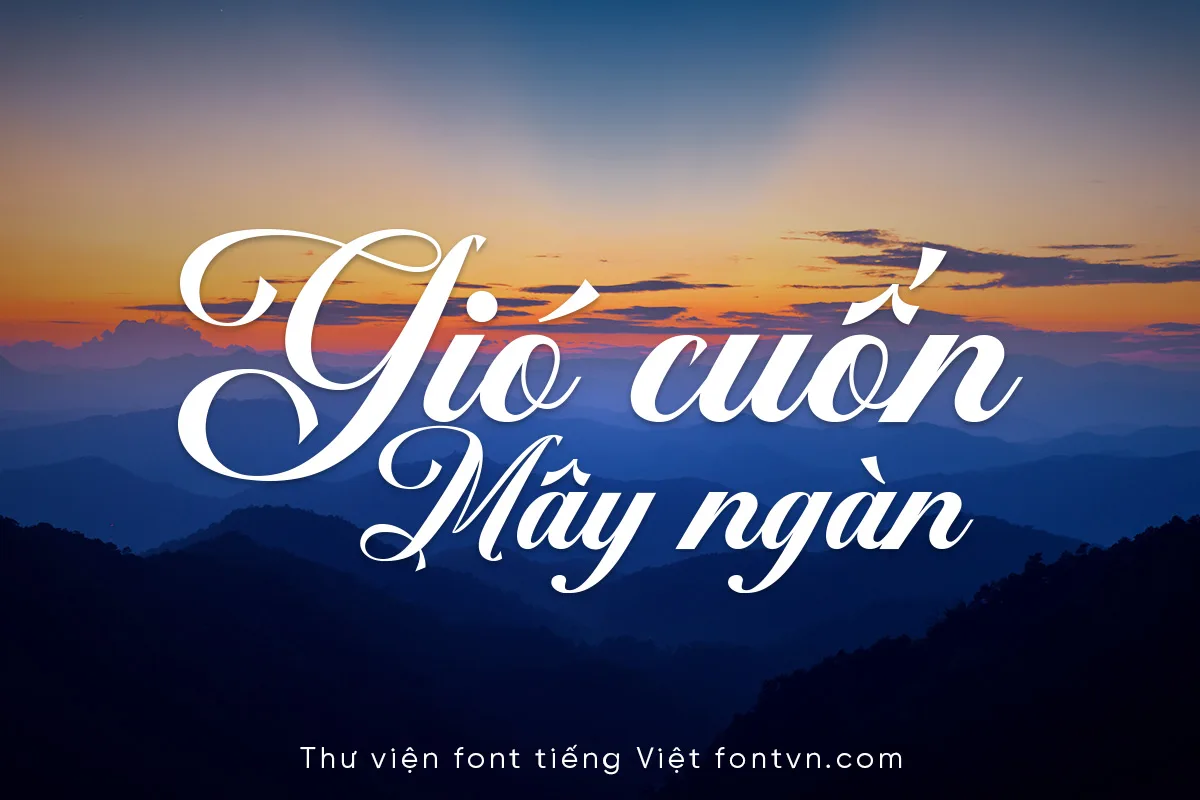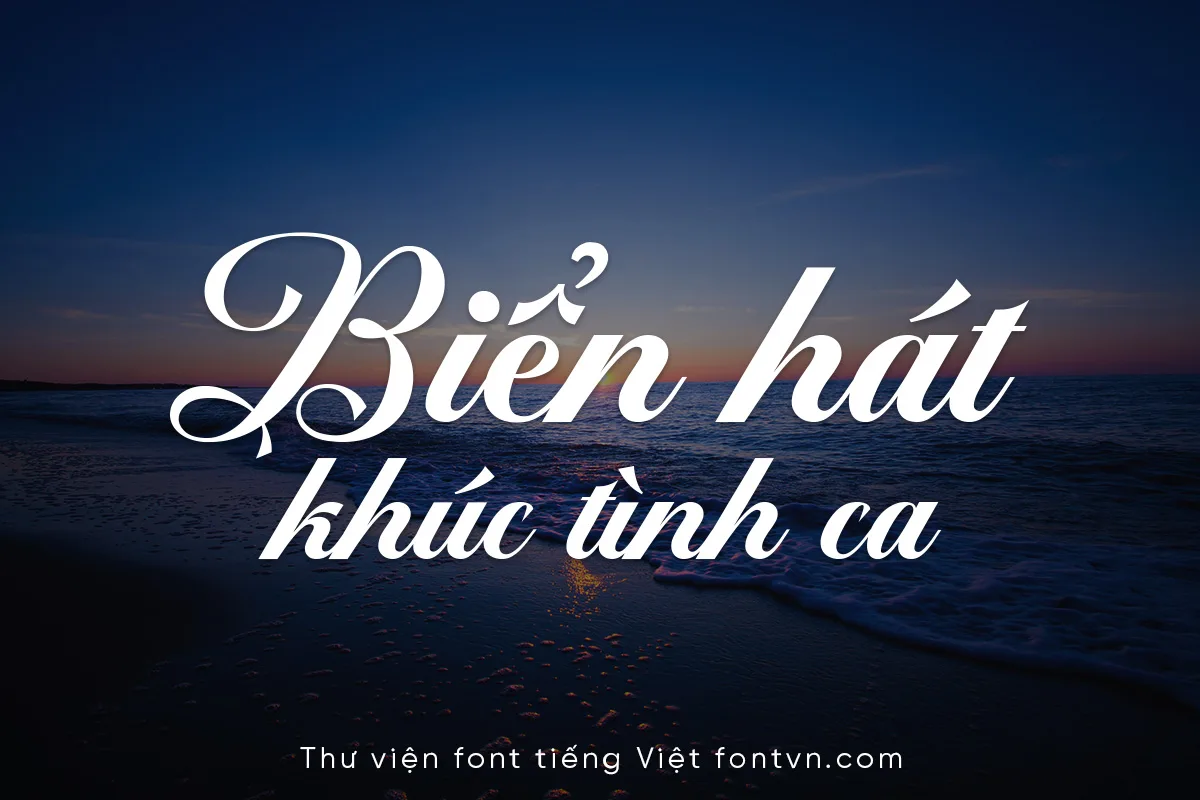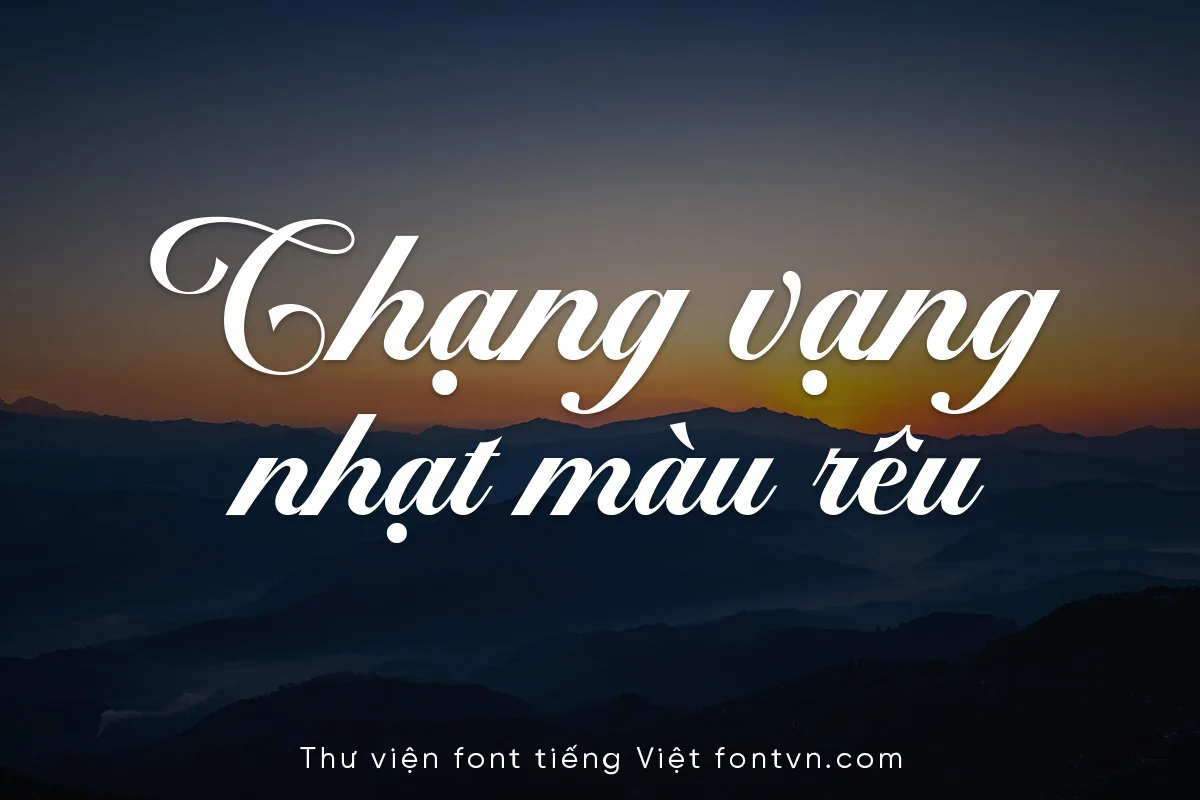
DVN Flentino – Font Chữ Script Với Những Đường Nét Uốn Lượn Đầy Mê Hoặc
DVN Flentino là một phông chữ script mang phong cách calligraphy cổ điển và sang trọng, được thiết kế tối ưu hóa hoàn toàn cho tiếng Việt. Về mặt hình dáng, phông chữ nổi bật với độ tương phản sắc nét giữa các dải thanh đậm, kết hợp cùng hệ thống đường nét uốn lượn (swash) mở rộng với biên độ lớn ở các ký tự in hoa nhằm tạo điểm nhấn thị giác thu hút. Cấu trúc của các ký tự in thường duy trì độ kết nối mượt mà, đi kèm với bộ dấu tiếng Việt được tinh chỉnh khoảng cách tỉ mỉ để đảm bảo tính dễ đọc (legibility), giúp tổng thể chữ luôn liền mạch và không bị chồng chéo ngay cả khi dàn trang với những đường nét phức tạp.
Nhờ sự cân bằng giữa tính thẩm mỹ nghệ thuật và cấu trúc thiết kế chuẩn mực, DVN Flentino là giải pháp typography đặc biệt phù hợp cho các dự án thương mại đòi hỏi sự cao cấp. Phông chữ này phát huy tối đa công dụng khi ứng dụng vào thiết kế nhận diện thương hiệu (logo), hệ thống bao bì nhãn mác cho các sản phẩm thủ công, mỹ phẩm, F&B (như bánh ngọt, nước ép), cũng như các ấn phẩm sự kiện trang trọng như thiệp cưới hay tiêu đề chiến dịch quảng cáo. Bằng những đường nét tinh tế, DVN Flentino giúp truyền tải sự chuyên nghiệp và nâng tầm giá trị thị giác cho mọi ấn phẩm.